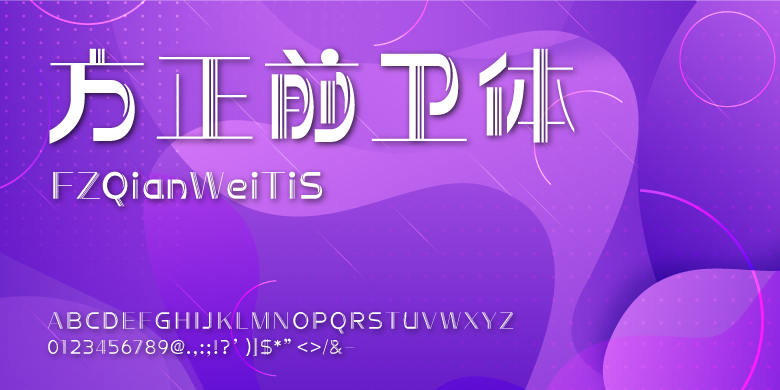
方正前卫体系列
方正字库, 设计师:郭炳权, 发行时间:2019, 字库编码:大陆简体(GB2312-80)、,简繁扩展(GBK), 分类:创意字体,
字体介绍:
方正前卫体由郭炳权先生创作,创意源自一个外国珠宝公司的商标,充满尖端时代特质,颇具迷人、诱惑和动感的气息。共包含8款字重,适合年轻、时尚和科技类宣传和包装设计。